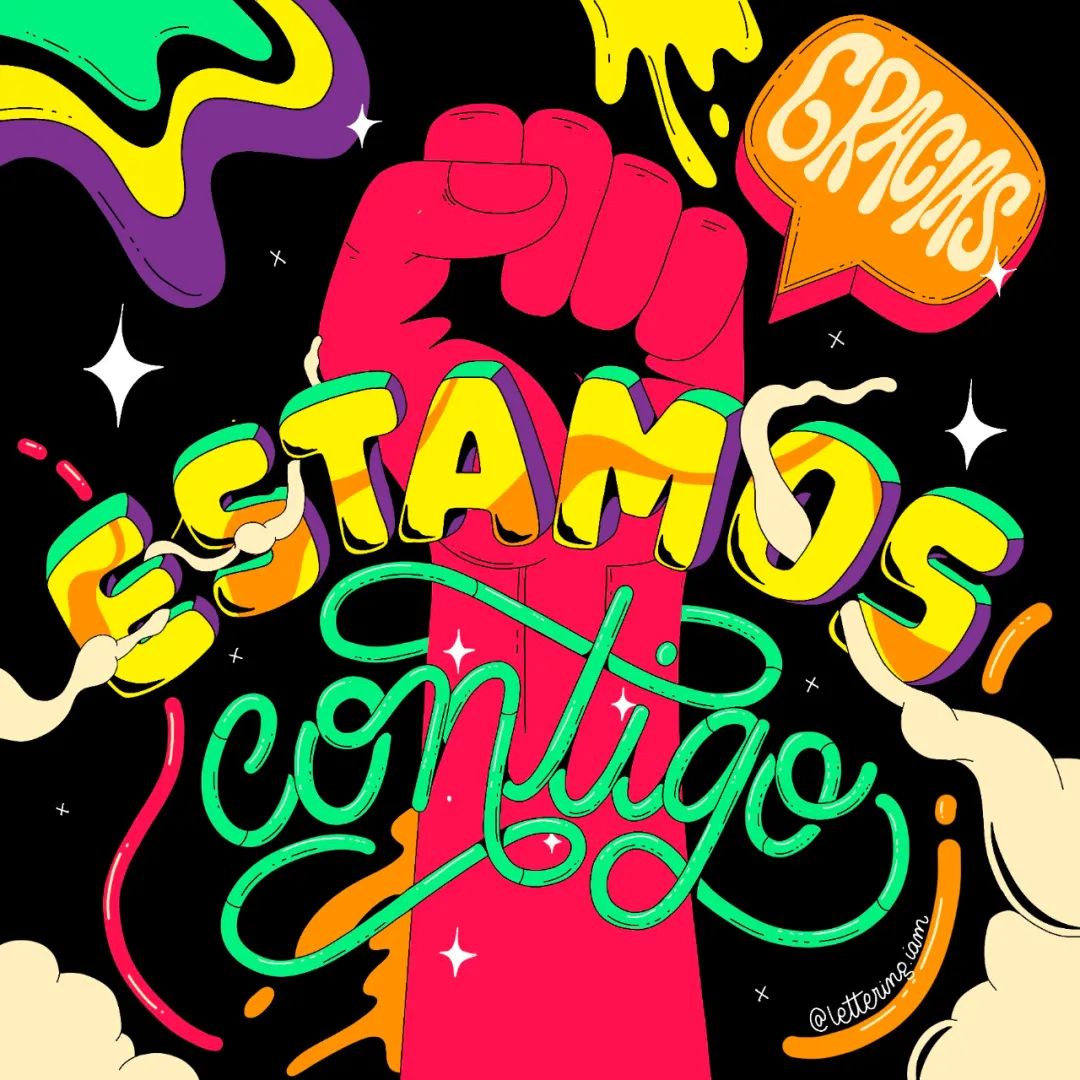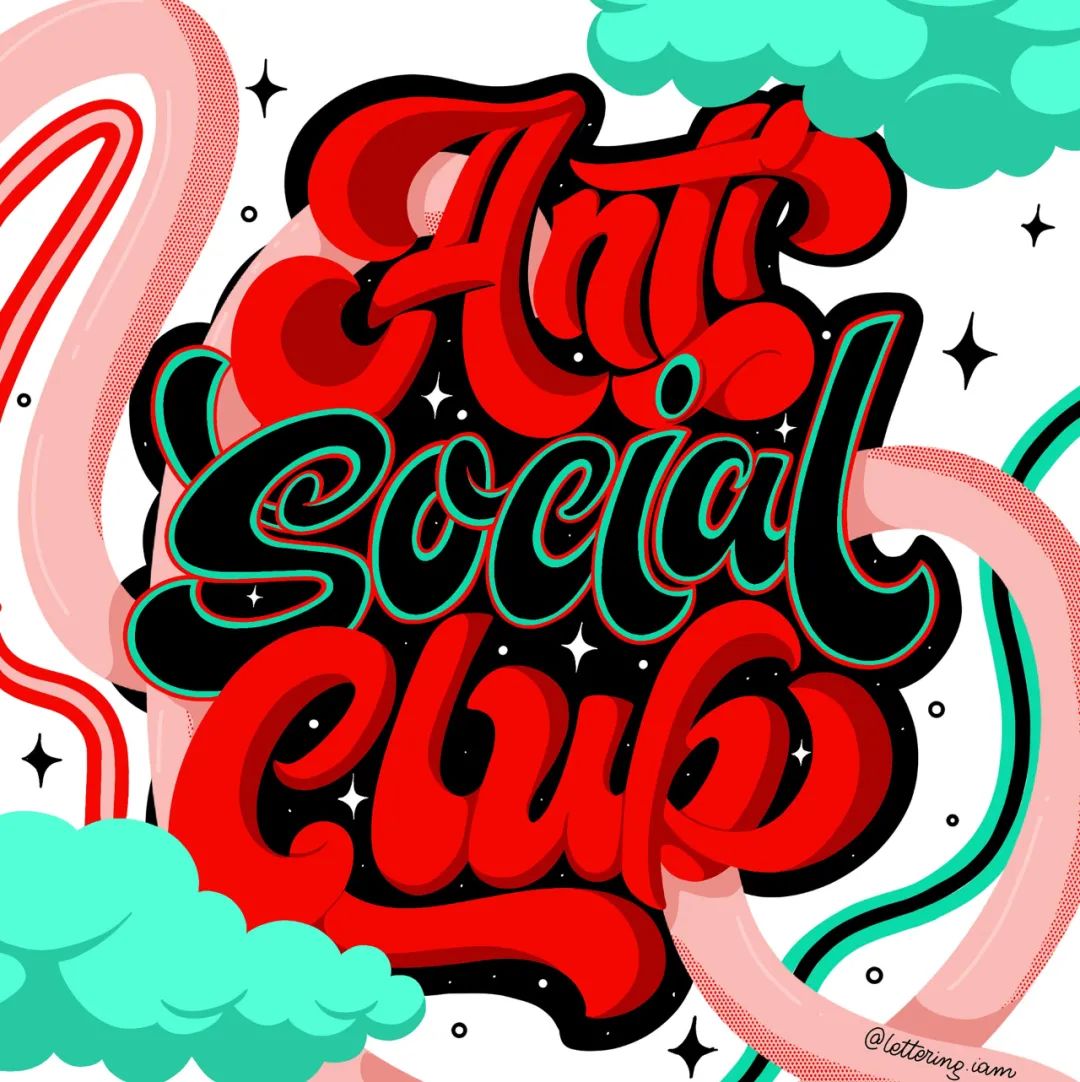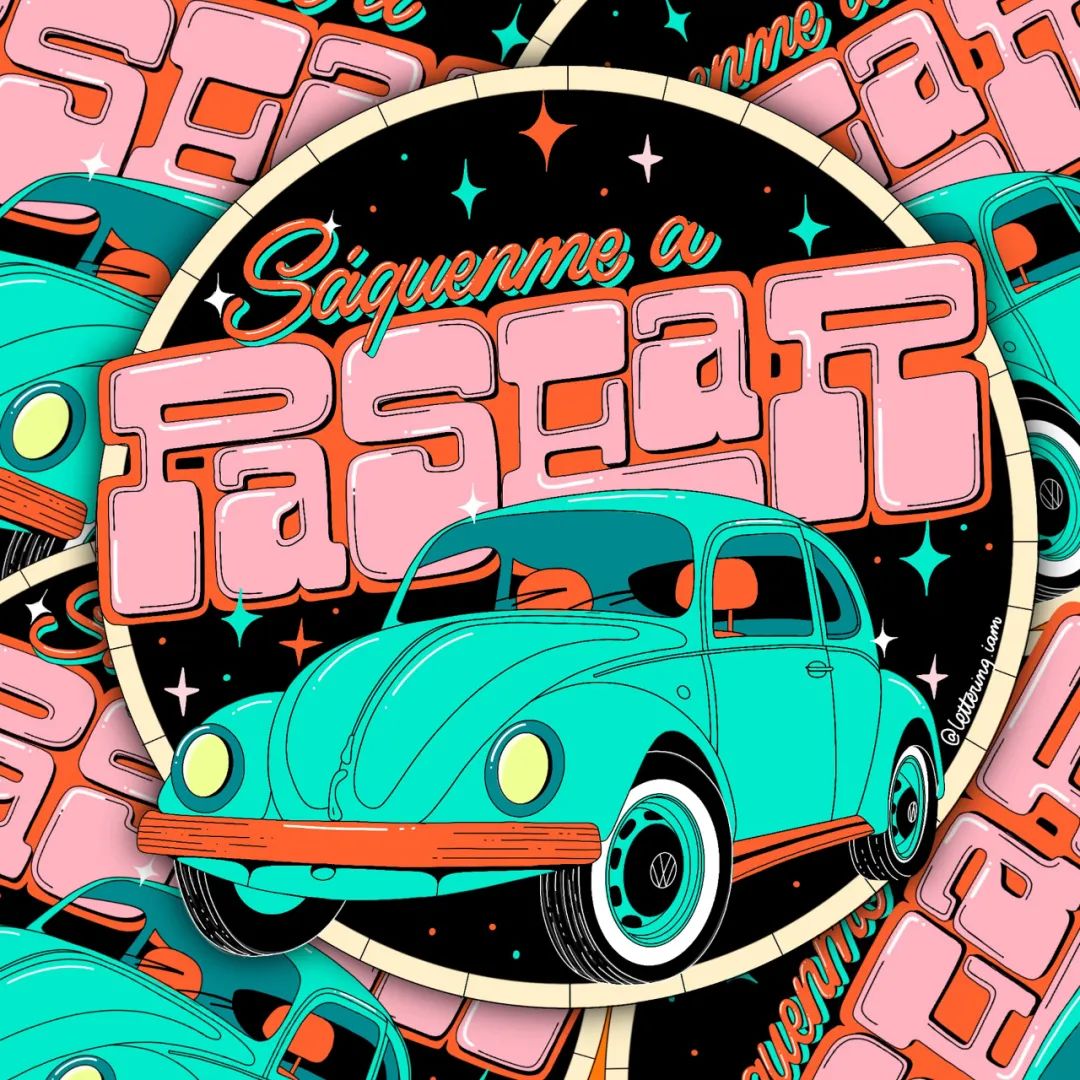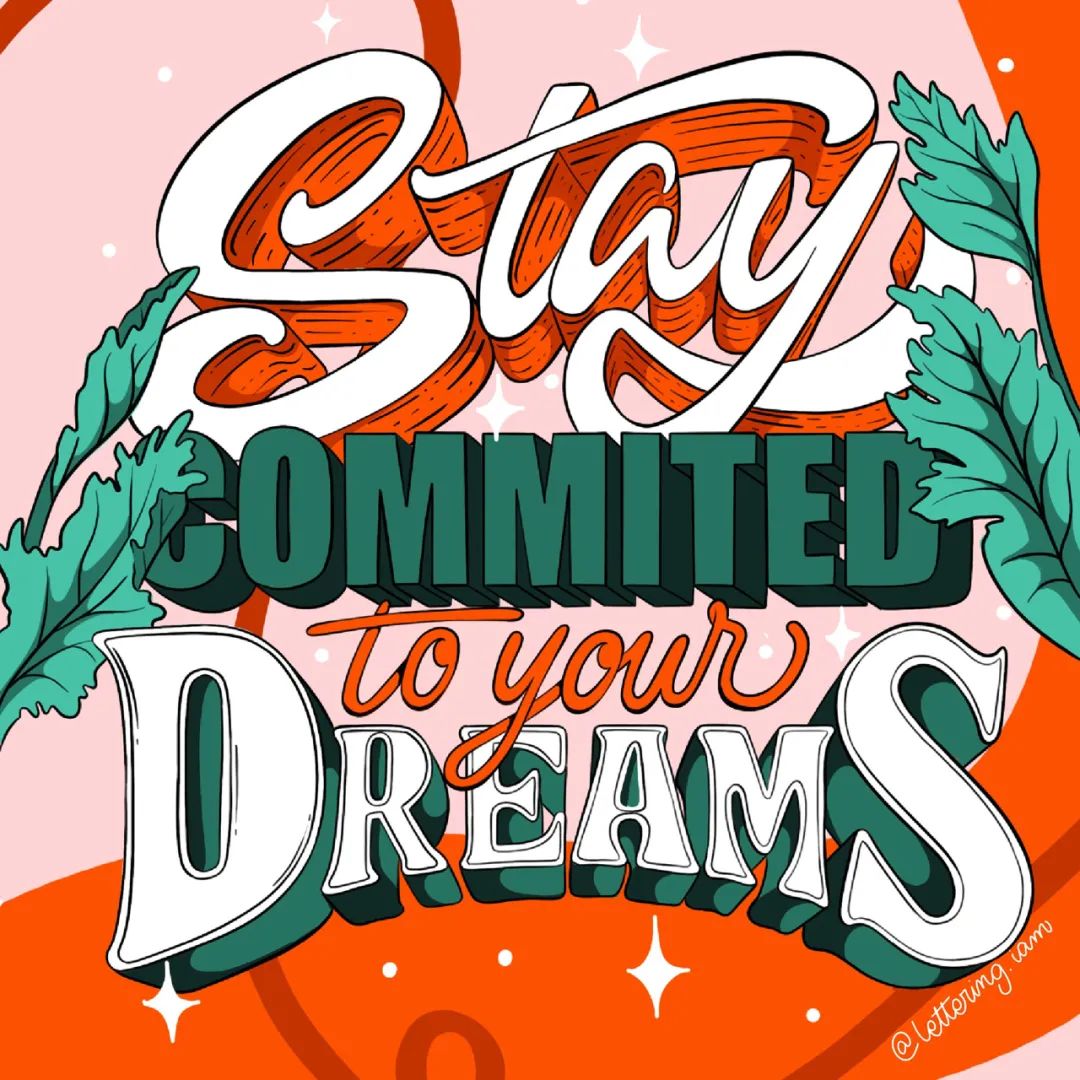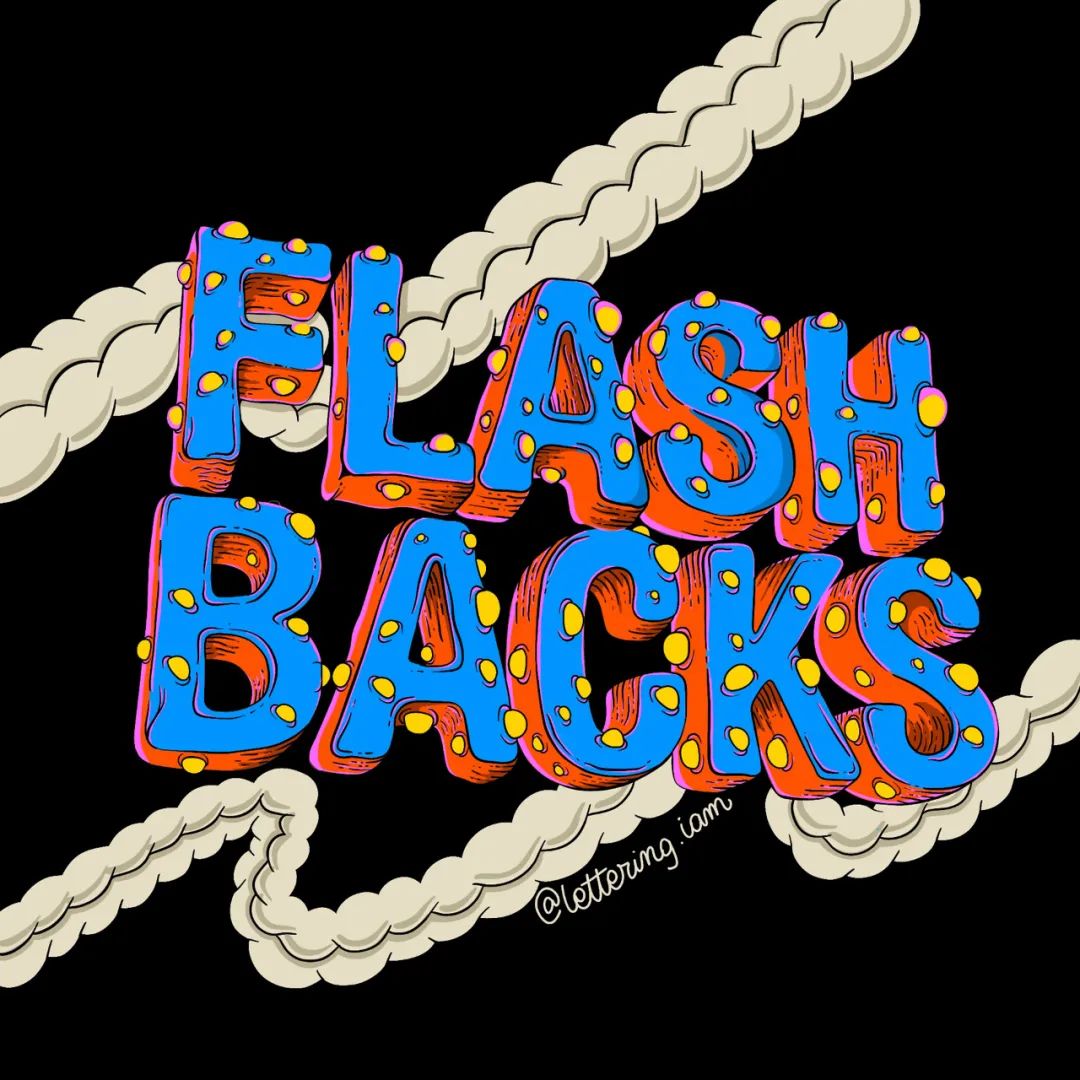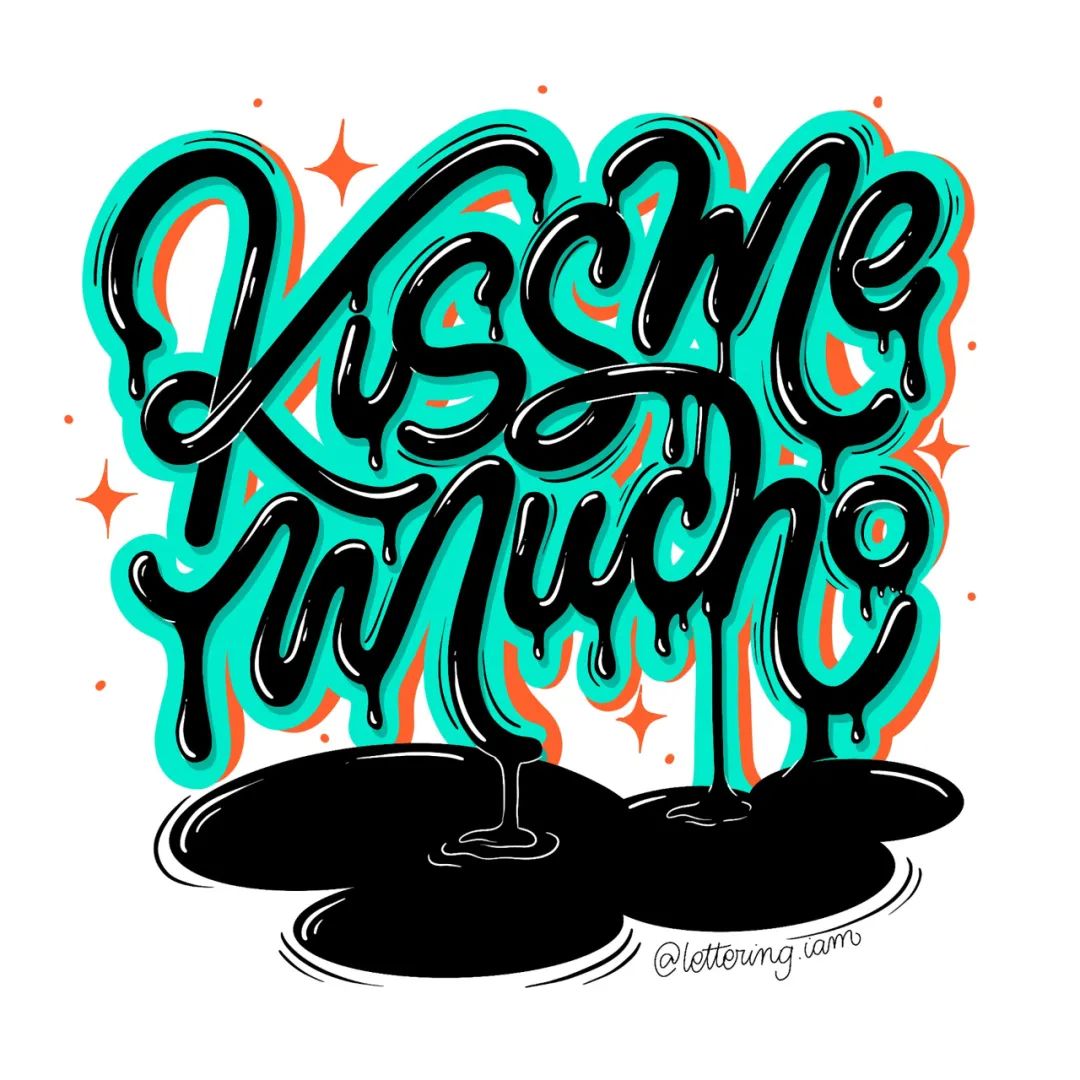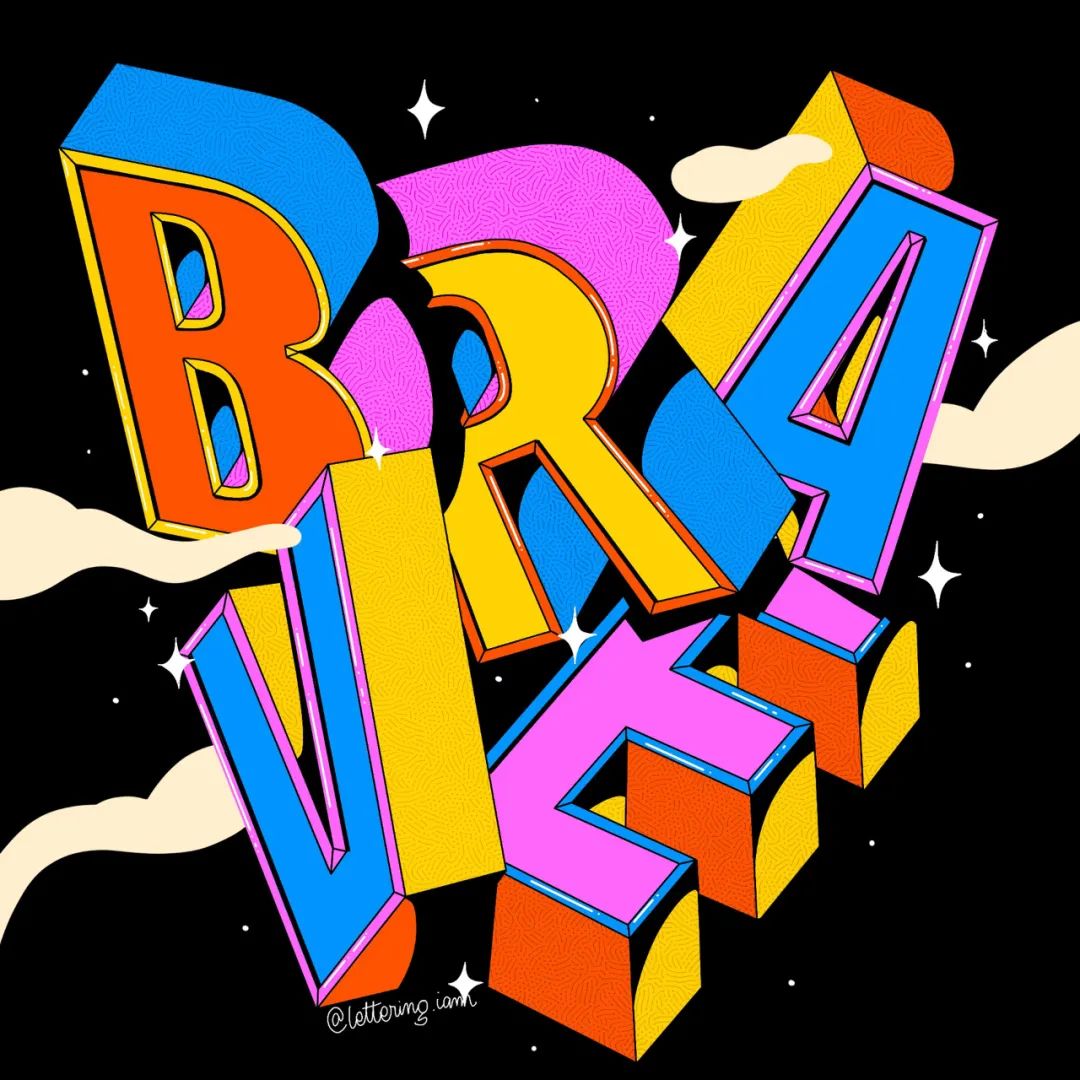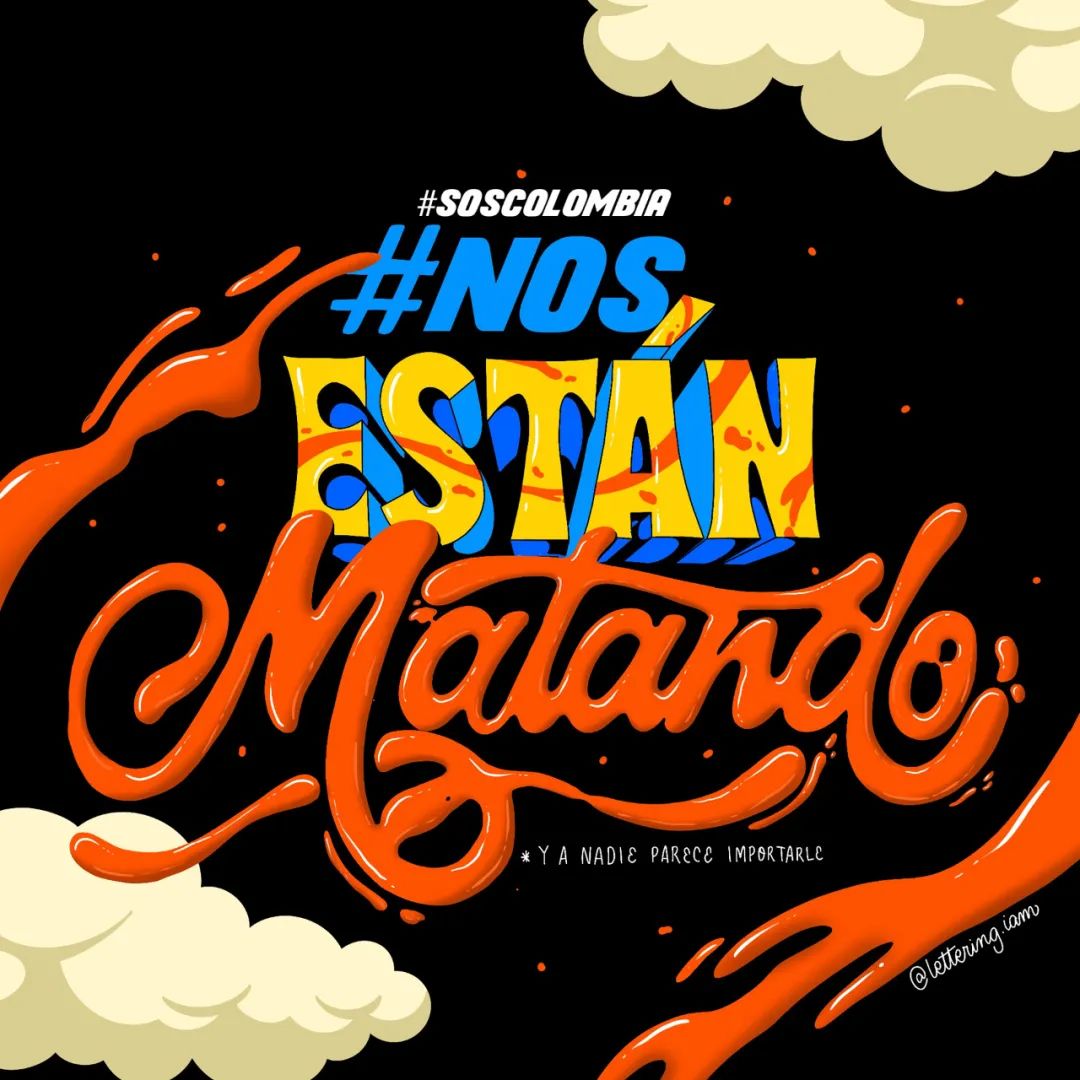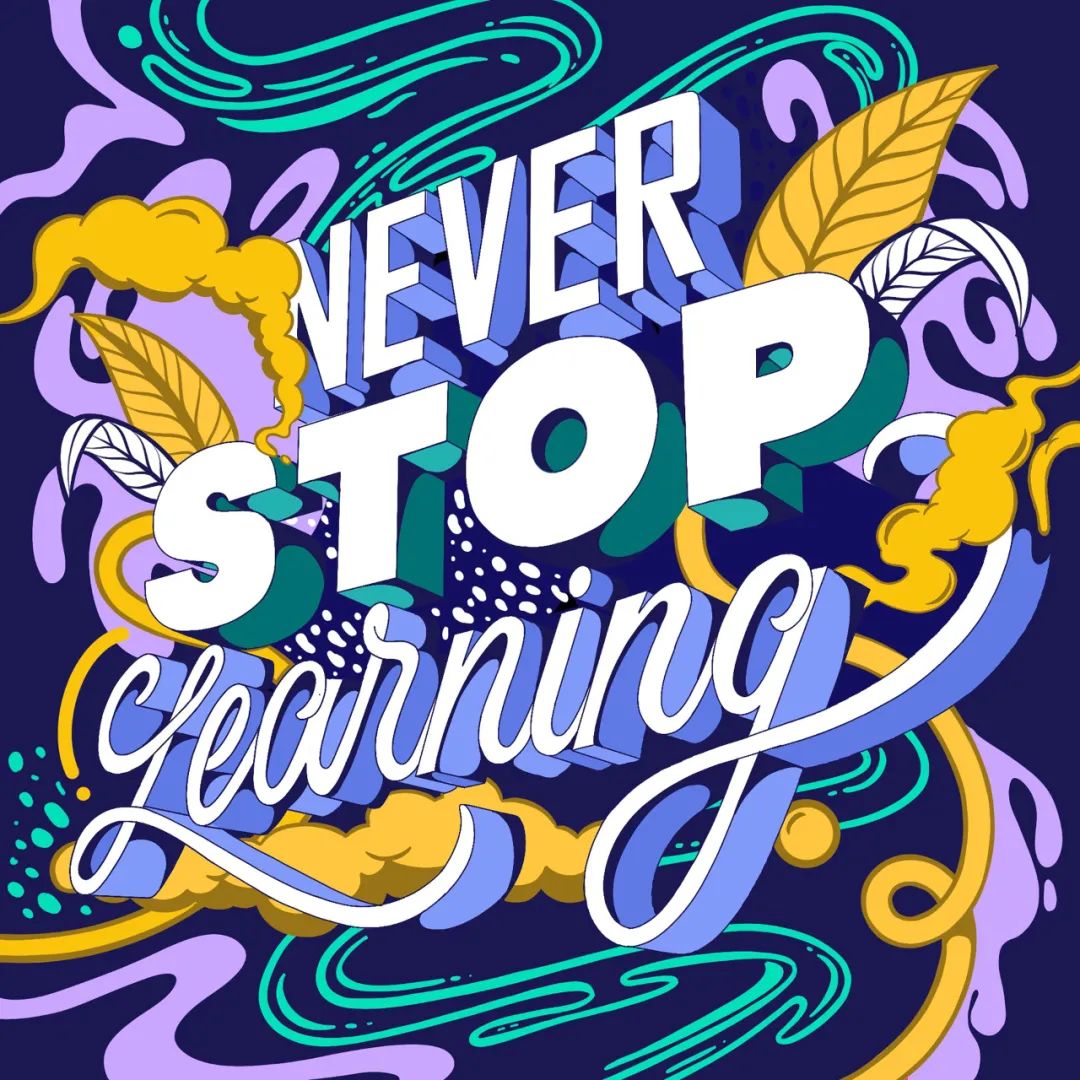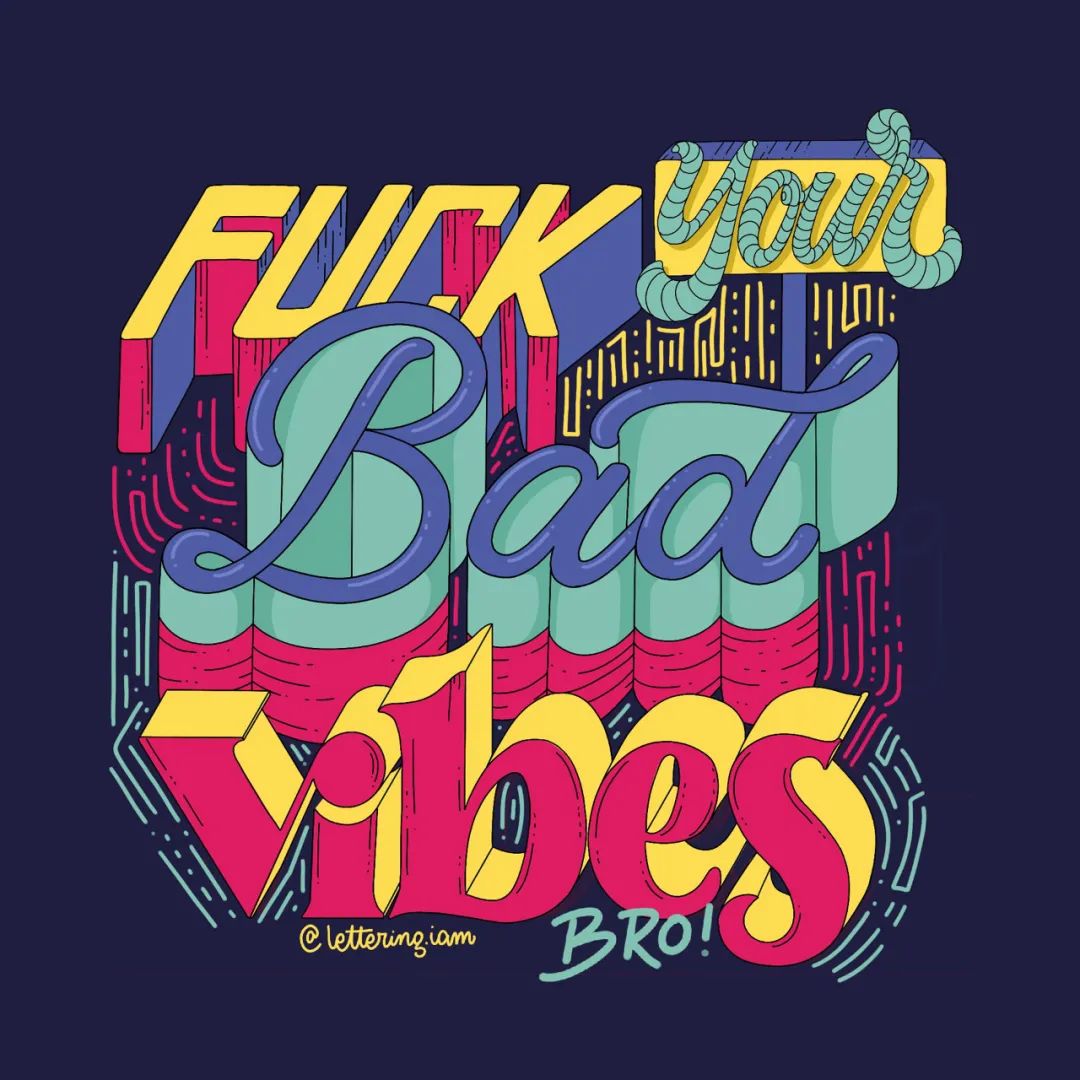
自学成才,5年前她喜欢上了字体设计!
今天要同大家介绍一位来自哥伦比亚的字体设计师与插画师:Ana Moreno。
在她所有的社交媒体上,她认为自己是一名工业设计师(或者至少她的文凭是这么说的),但她却一直在平面设计领域工作,因为这是Ana Moreno一直喜欢的。五年前她发现并喜欢上了 Lettering,从那时起,她意识到这就是为什么她每天早上醒来都会充满肾上腺素的原因。
Ana Moreno 以一种自学成才的方式开始了这条路。看,做,临摹。当她要求更多的时候,发现了自己的风格,并开始对歌词和背后的“科学”进行更多的字体研究。她的工作使她与环球音乐、潘多拉和哥伦比亚品牌进行了多次合作,以及美国和哥斯达黎加的一些小品牌。还在萨尔瓦多的《黑人曼巴》杂志和伊比利亚-美洲插图索引等出版物上发表文章。
接下来,将通过她的作品一起来了解她的字体设计风格。
先看第一个作品。
这是她为她的instagram帐户制作的一些作品汇编。它们有不同的字体风格和一些插图,跳跃的颜色和灵动的线条,只是为了好玩!
看下第二个作品,这是其为一个茶品牌设计的一个商业项目。
Kombuchaz!是一个寻求在市场上展示自己作为一个有趣的茶品牌。他们想用三种口味的茶来展示年轻人可以分享的有趣时刻,比如:海滩、运动或聚会。Ana Moreno 通过字体及插画的方式,在这3个标签上进行体现。‍
Instagram贴纸
他们希望利用标签上的插图,让消费者有可能在Instagram的故事中使用它们,分享他们喝茶的时刻。设计上使用了调皮的图形与文字。
第三个案例,是字体插画在书籍封面上的应用。
这一次,她想根据她最喜欢的一些电影设计一套书(尽管有些是电影之前的书)。Ana Moreno 想用字母重新设计标题,整个插图都是基于她对每部电影的看法,还分享了其线稿到色稿的过程图片。
再看看其在2019年的 Lettering collection,非常有意思的字体创作与视觉表现。
2019年5月,哥伦比亚 ‍El Guayabo咖啡馆邀请 Ana Moreno 在它们的入口墙画一幅壁画。上面写着:“Como en el solar de tu casa meeejo”,这是一种邀请人们进来的方式。最终通过12个小时,Ana Moreno 完成了这个项目。
通过一个1分钟的视频,来看下过程。
同年11月份,Carvajal Espacios 联系她,要她在他们位于卡利市的新展厅上画一幅壁画。这个想法是用他们的口号“Creamos espacios pensando en ti”来装饰他们的空间。